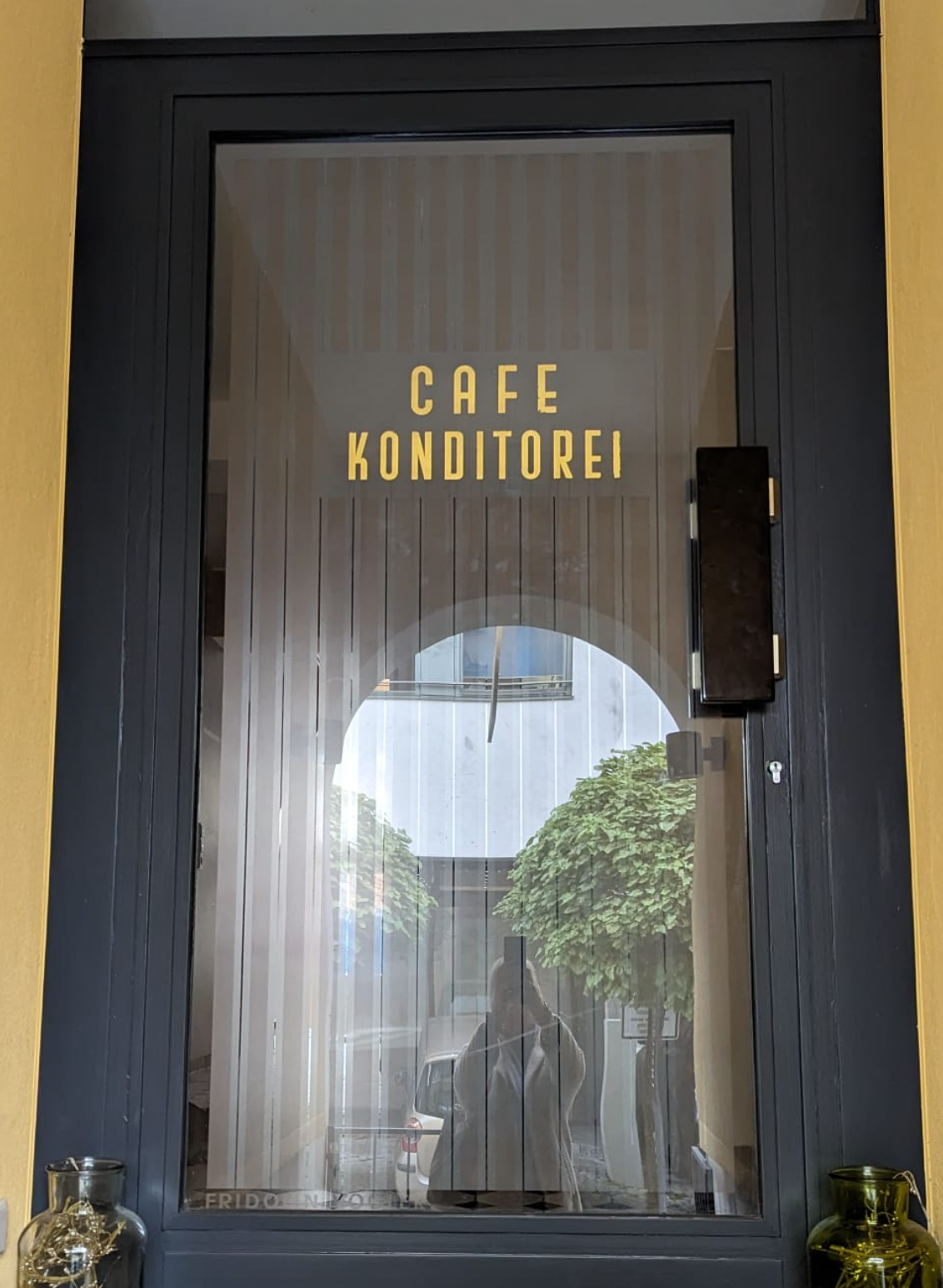
Welche Schrift ist das? Schrift von einer Eingangstüre
ich bin auf der Suche nach der Schrift die auf einer Eingangstüre zu einer Konditorei verwendet wurde. Ich vermute es geht in die Richtung Art Deco. Kann mir jemand weiterhelfen? Wäre sehr hilfreich.
Ich habe persönlich nachgefragt beim Eigentümer und die Schrift wurde tatsächlich von hand entworfen und gecuttet. Das war noch arbeit :-)